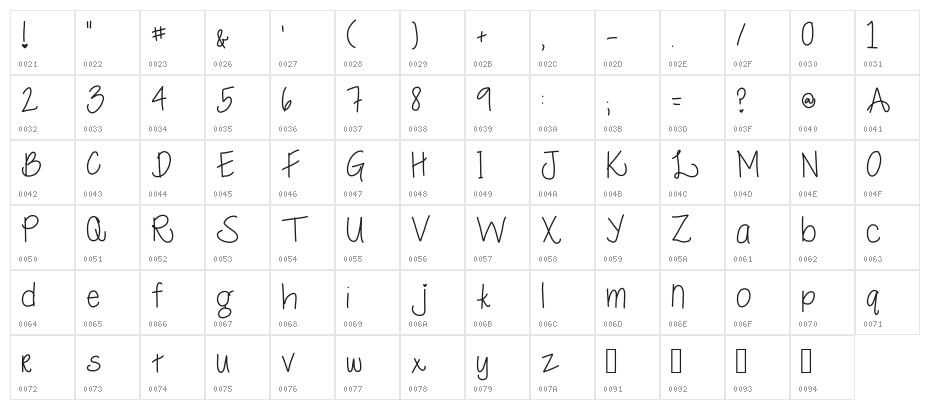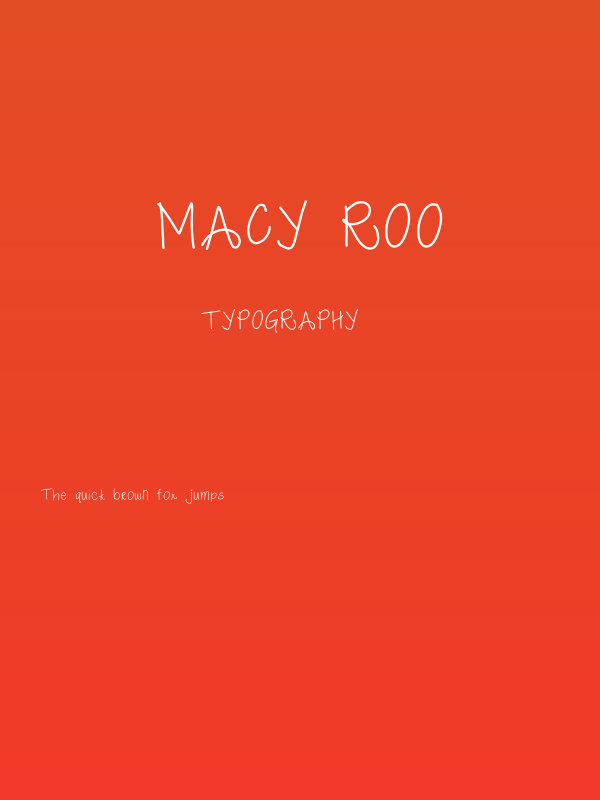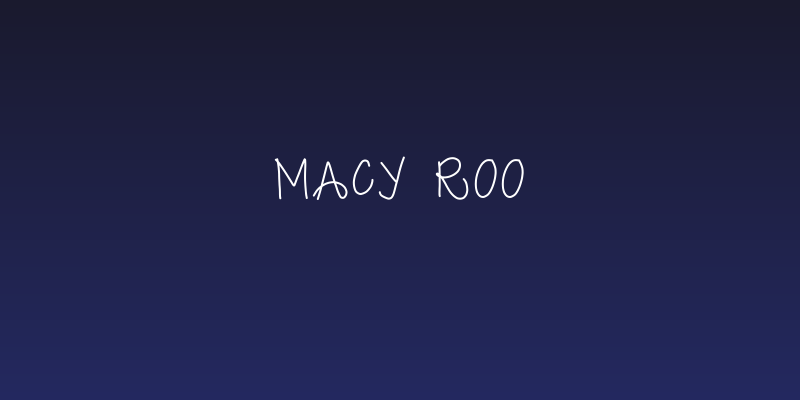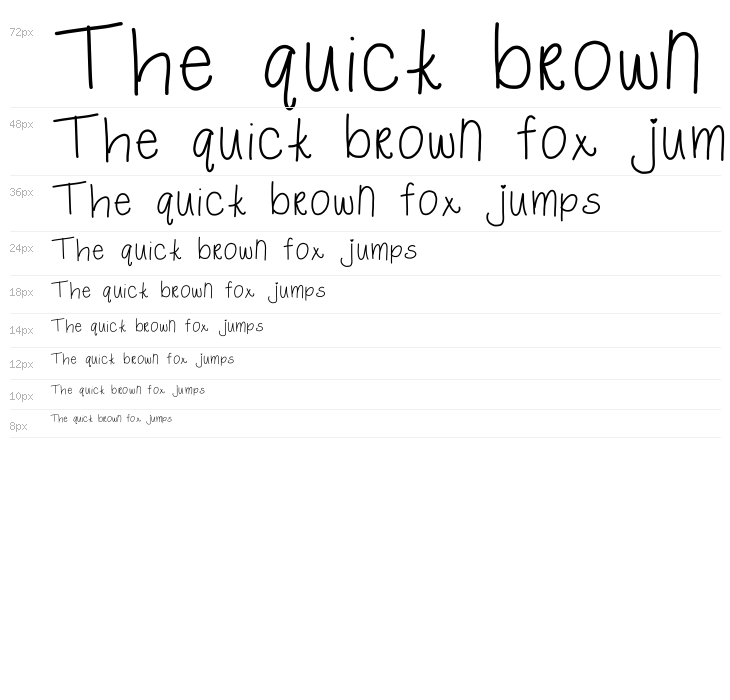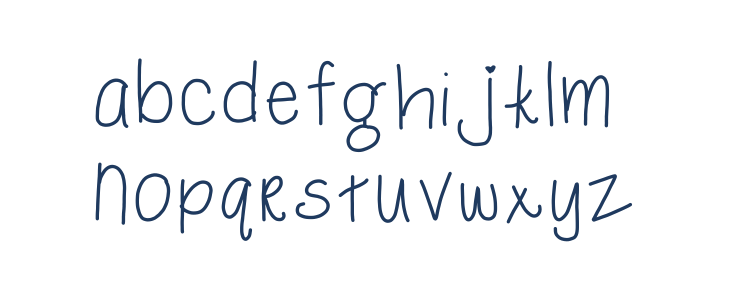
Macy roo Font
| Gesamtstil | Casual |
| Anwendungsfall | Headlines, Informal text, Creative projects |
| Vorgeschlagene Projekte | Ideal for greeting cards, children's books, casual invitations, and social media graphics. |